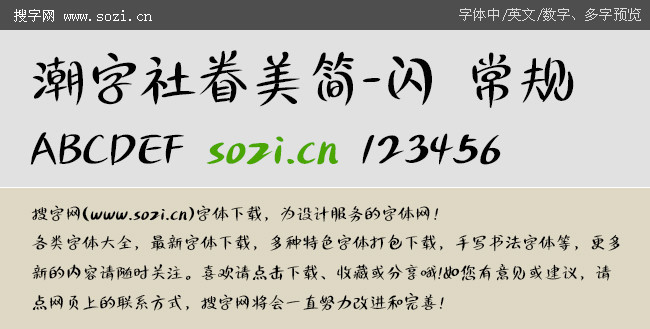
潮字社眷美簡-閃 常規(guī)
搜字網(wǎng)提供一款潮字社眷美簡-閃 常規(guī)中文字體下載,潮字社眷美體是一款線條優(yōu)美圓潤的藝術(shù)字體,風格比一般的字體更有特色,連貫字跡顯得干練而不凌亂,清新簡明,具有很好的視覺感,適合應用于藝術(shù)設計、平面宣傳設計、網(wǎng)頁設計等領(lǐng)域等應用。(本字體為個人非商用版,商用請聯(lián)系作者購買授權(quán))